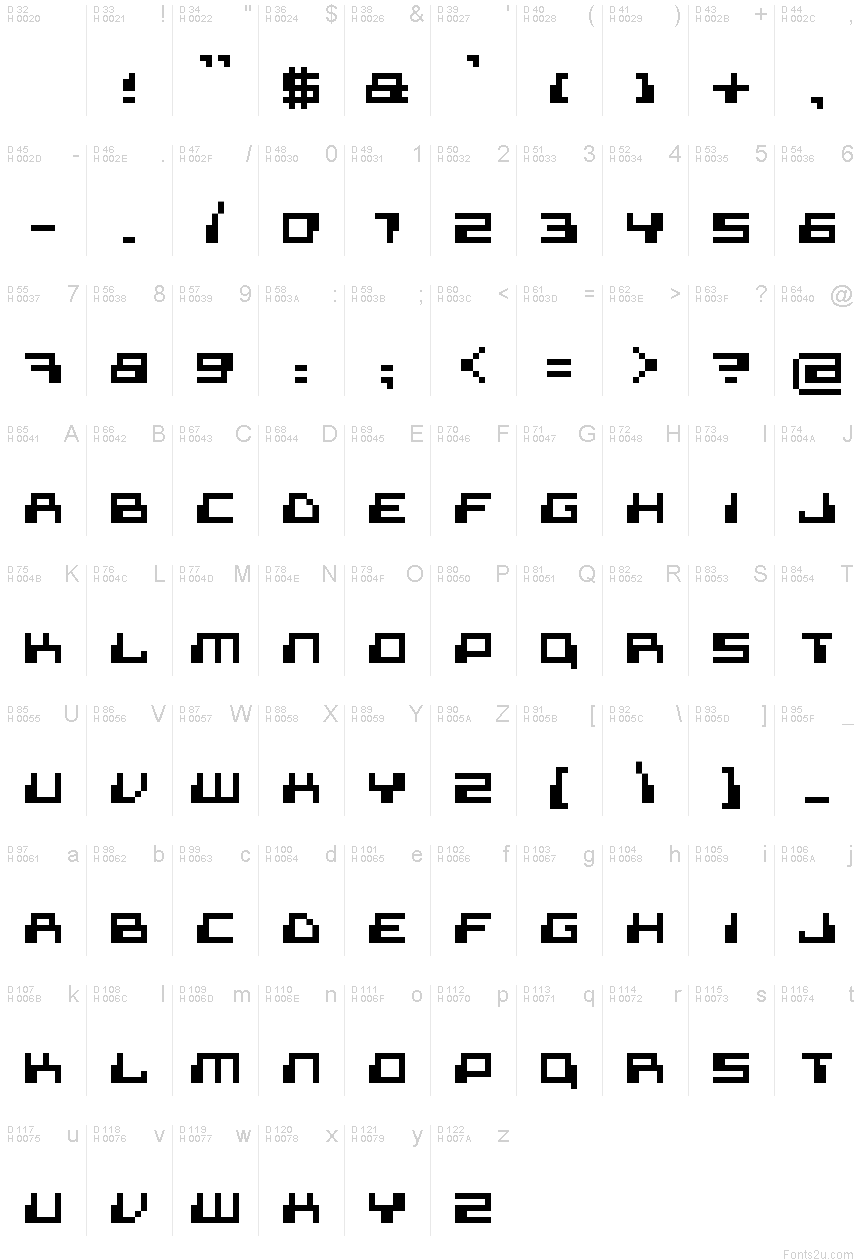
Superdigital je bezplatný pixelový bitmapový font od Superlooper, postavený na strohém rytmu rané počítačové grafiky. Písmena jsou robustní a modulární, s hranatými rohy, schodovitými křivkami a kompaktním arcade nádechem, díky kterému působí celý font ostře, synteticky a lehce hravě.
Přirozeně zapadne do herních menu, retro-tech plakátů, webových odznaků, záhlaví zinů a krátkých titulků, kde hraje hlavní roli právě ona nízkorozlišená textura. Jako font zdarma skvěle poslouží i na samolepkách nebo návrzích rozhraní, která vyžadují záměrně digitální vyznění. Držte se krátkých slov a úderných řádků, protože ten blokový vzor je přesně to, o co jde.